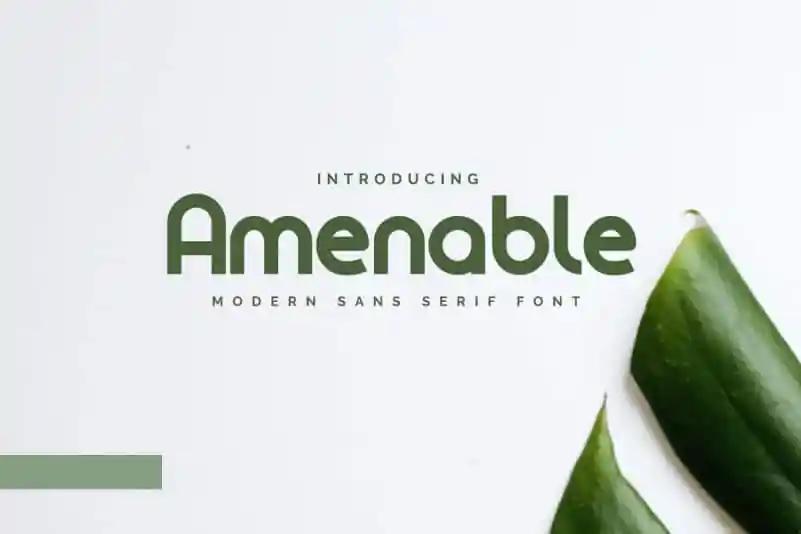
Introduzimos a Amenable Sans Serif Font, criada ao observar detalhadamente formas geométricas e ao focar na perspectiva do olho quando lêmos texto, para que a fonte se destaque como harmônica e confortável de ler. Este é um elemento essencial para quem busca uma fonte com aparência perfeita, capaz de tornar qualquer design impecável. Com o Amenable Sans Serif Font da twinletter, adicionar elegância e precisão à sua tipografia nunca foi tão fácil. Seja em relatórios, websites ou material gráfico, esta fonte singular é uma escolha óbvia para quem valoriza a simplicidade e a eficácia na comunicação visual.